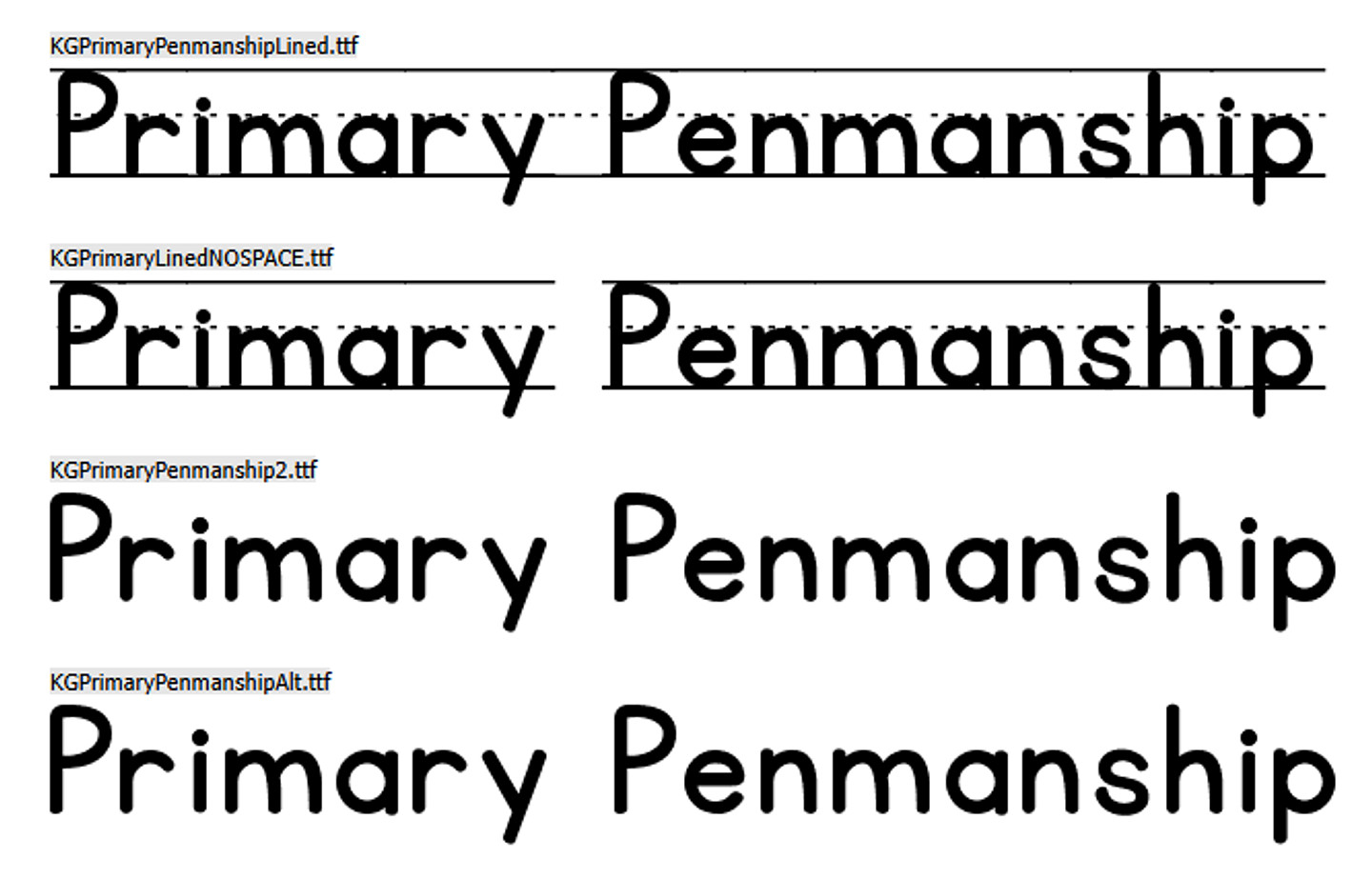
KG Primary Penmanship
위의 이미지는 손글씨로 보여집니다. 동일한 알파벳을 자세히 보면 조금씩 다릅니다. 이미자와 가장 유사한 폰트로 미국의 초등학교에서 가르치는 정자체 스타일과 매우 유사하여 이미지 속 글씨체와 비슷한 느낌을 줍니다. KG Primary Penmanship 폰트 라이선스 개인적 용도: 무료 학생의 과제, 개인적인 노트 필기, 비영리 목적의 개인 블로그 꾸미기 등 금전적 이득이 발생하지 않는 모든 활동에 자유롭게 사용할 수 있습니다. 상업적 용도: 유료 상품 로고, 유튜브 썸네일, 광고, 판매용 인쇄물 등 수익 창출을 목적으로 하는 모든 활동에 사용하려면 반드시 디자이너에게 유료 라이선스를 구매해야 합니다. 폰트링크 https://www.dafont.com/kg-primary-penmanship.font